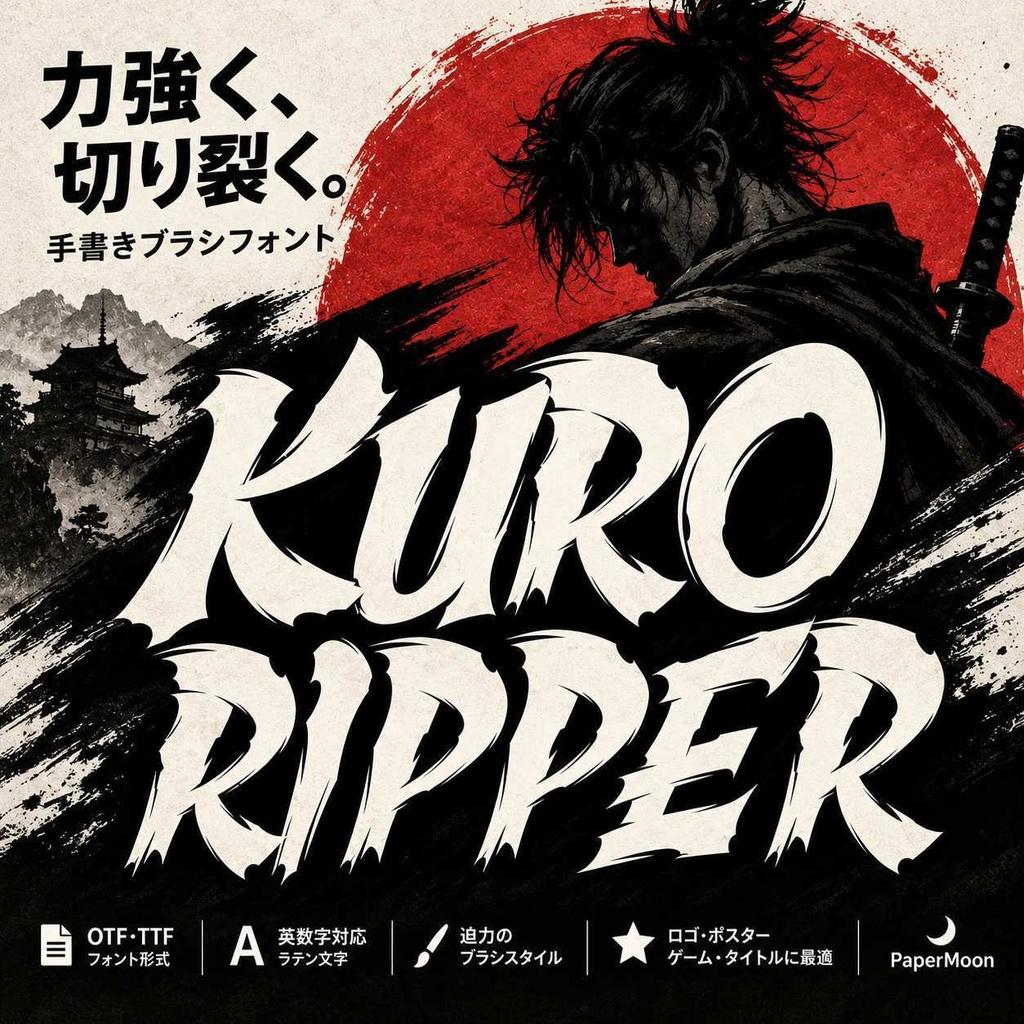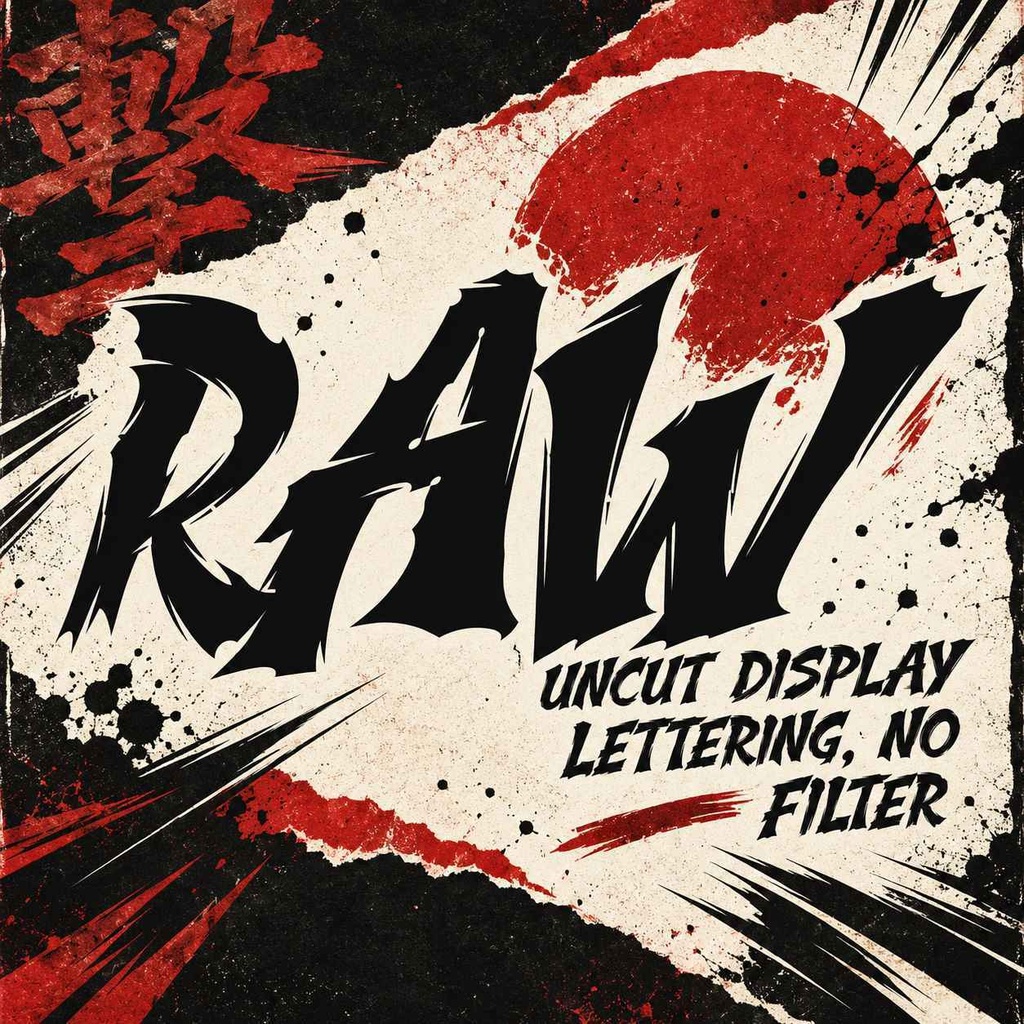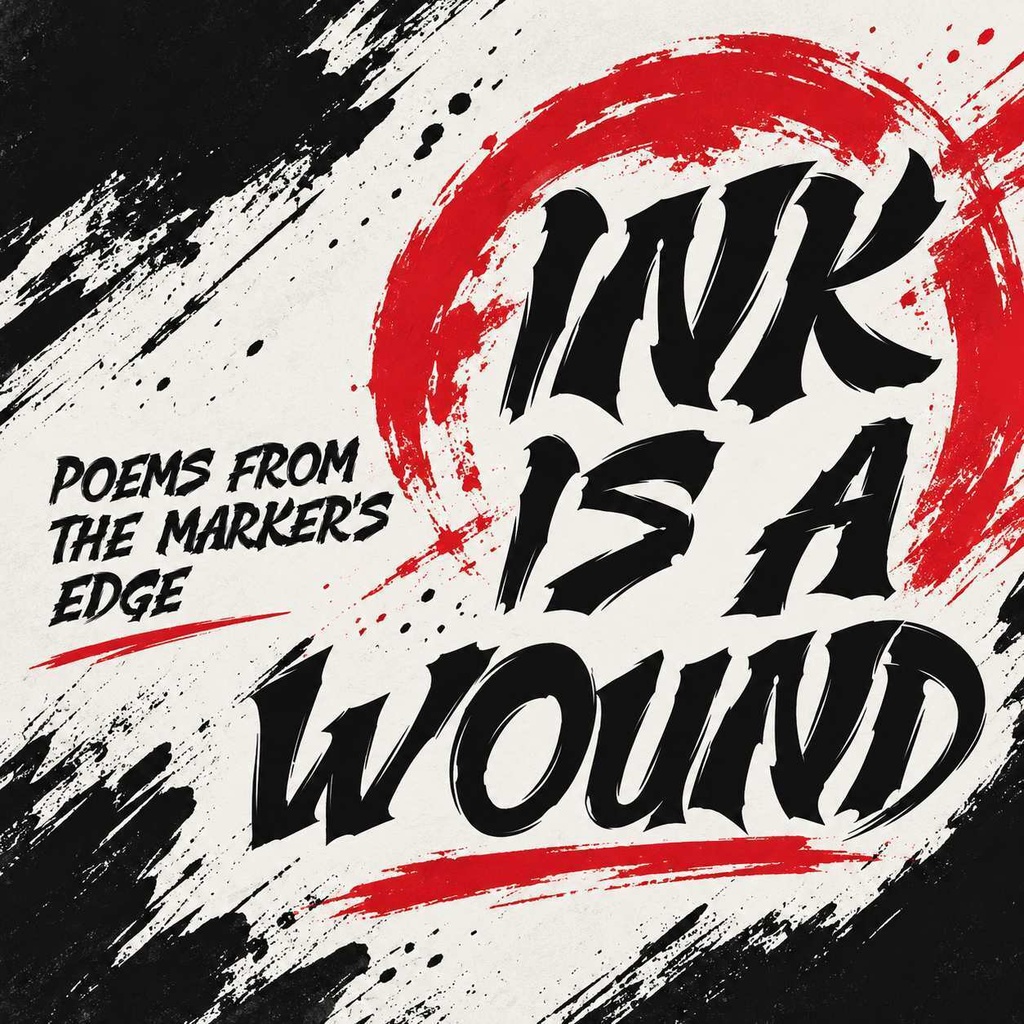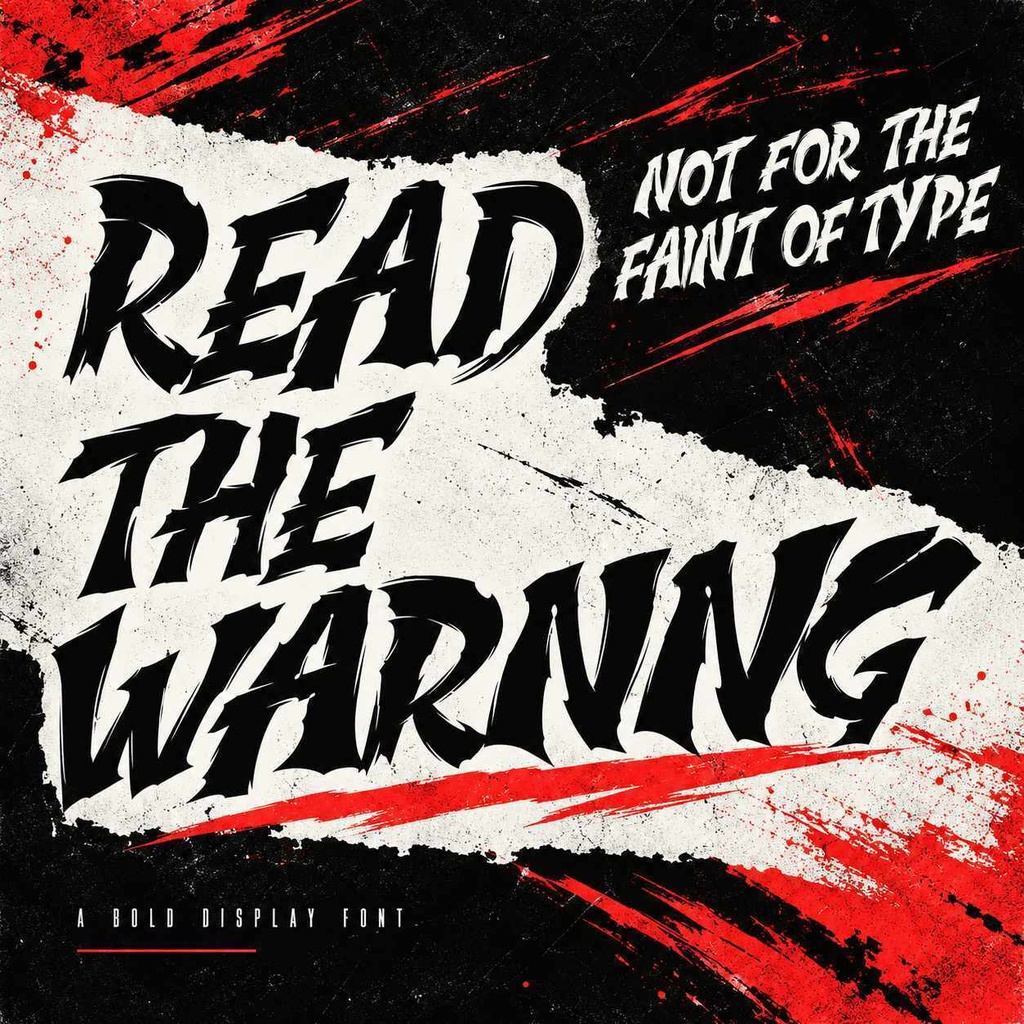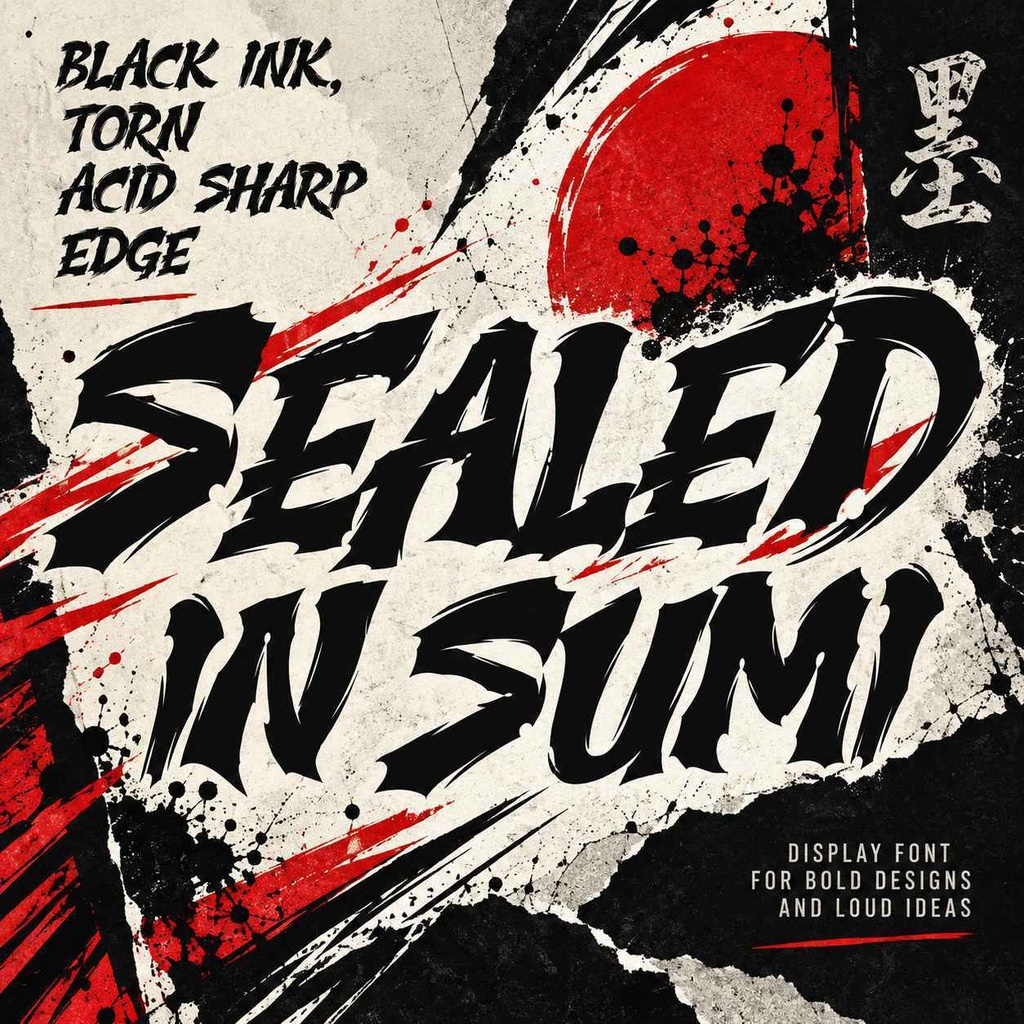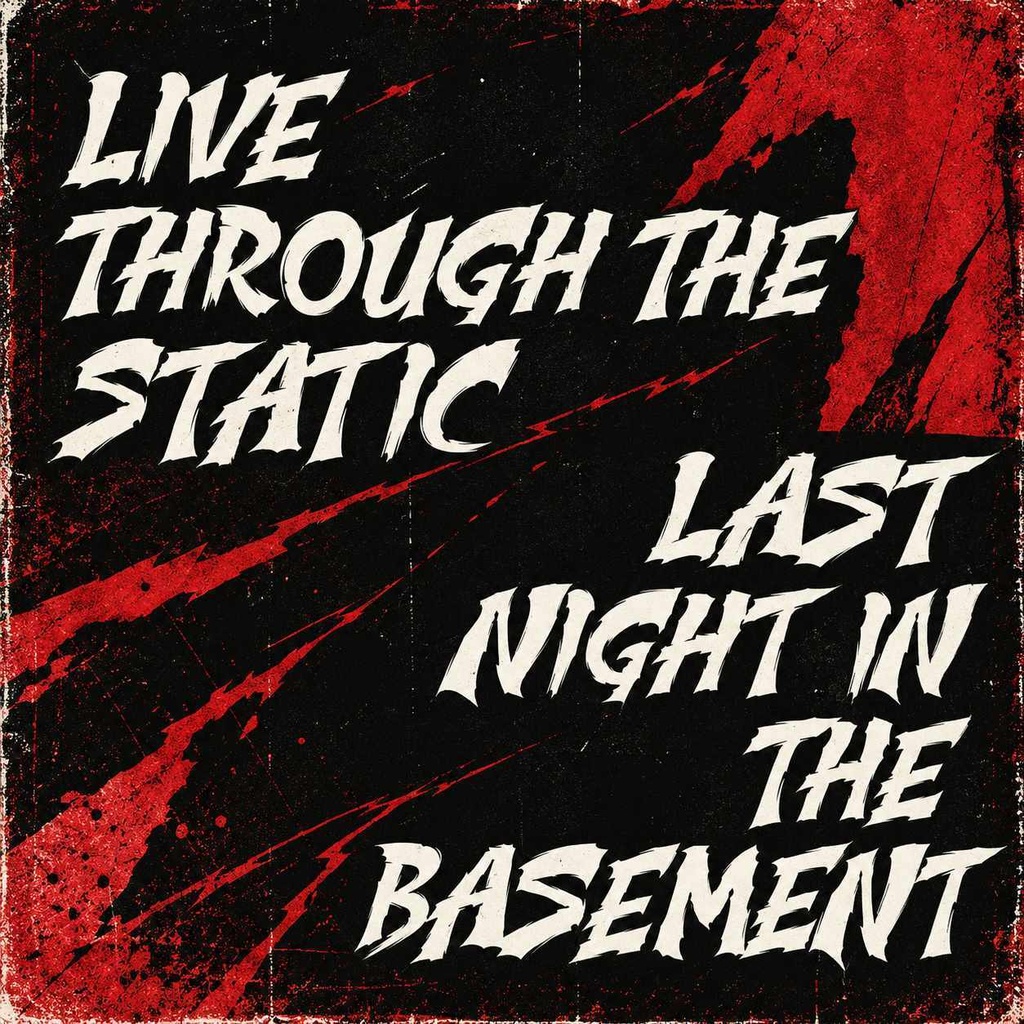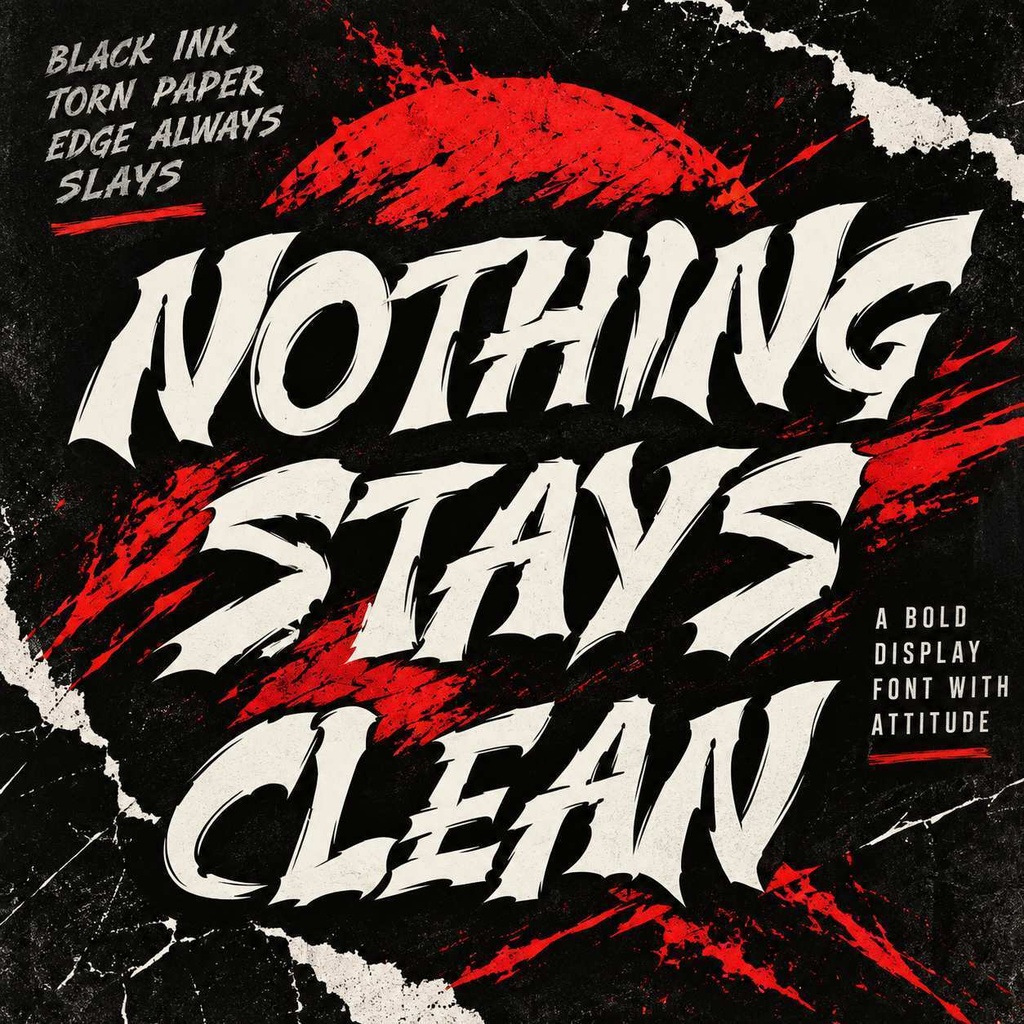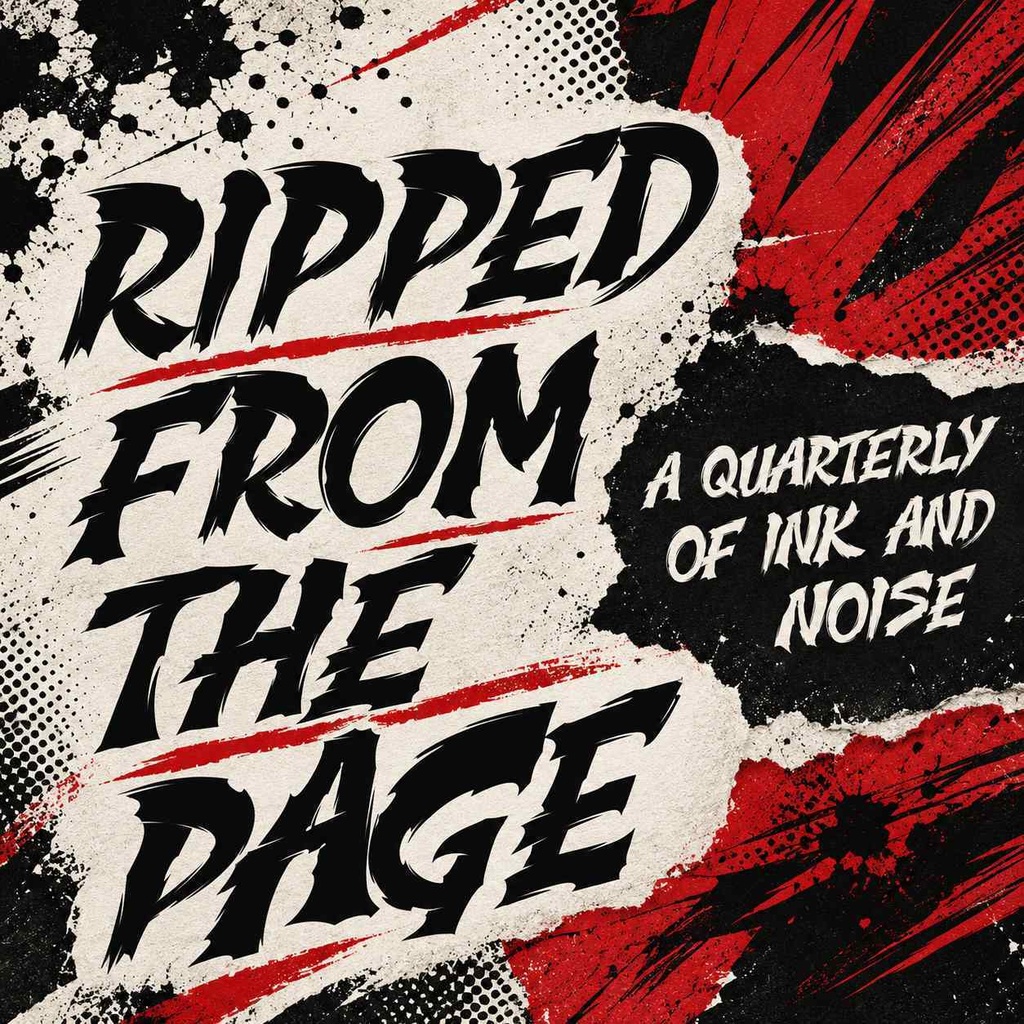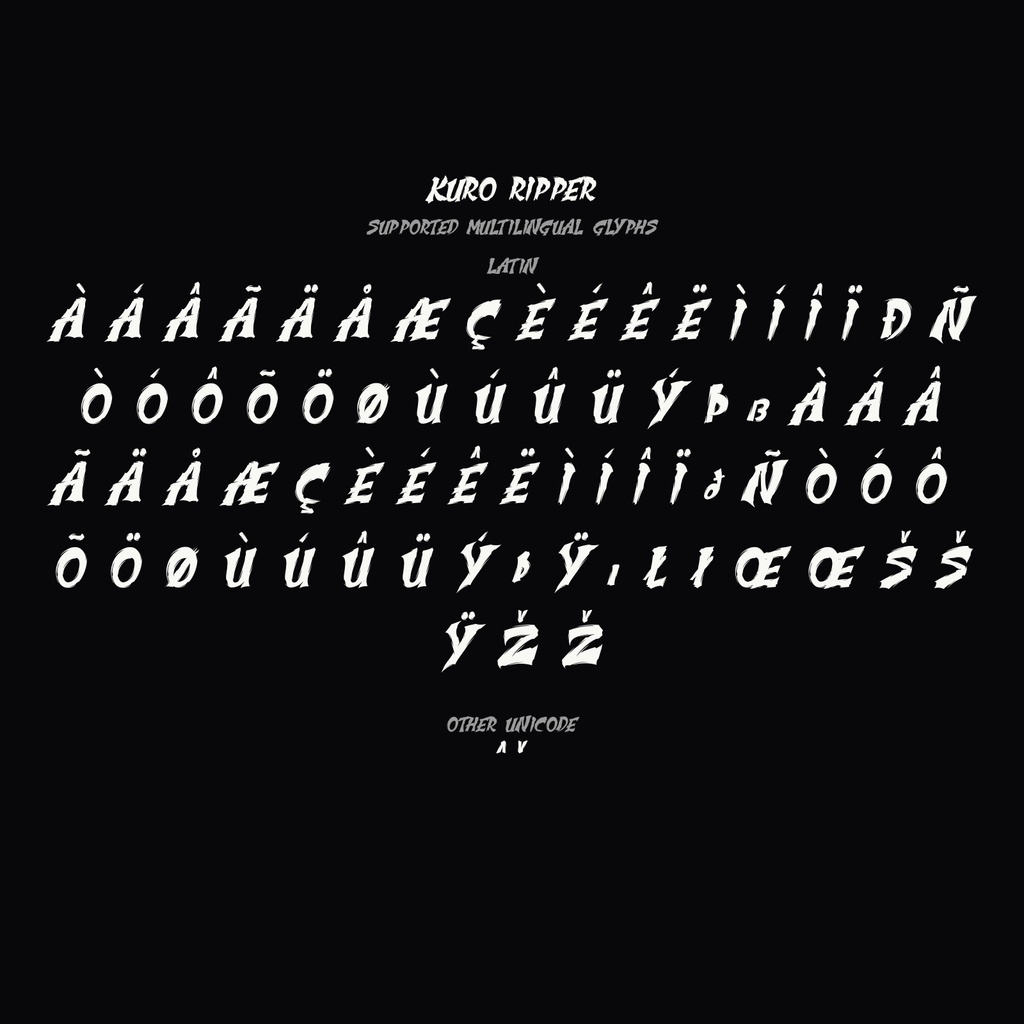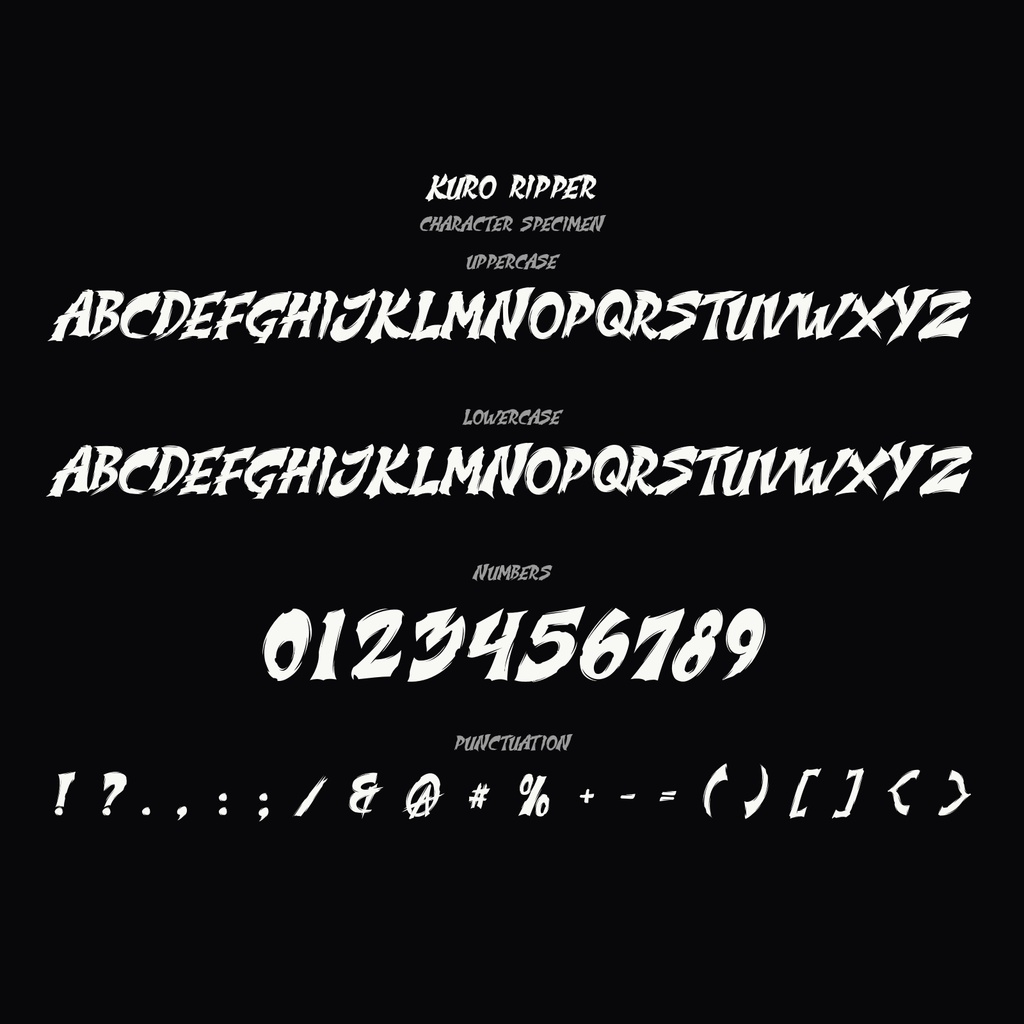
Kuro Ripper | ホラーマーカー欧文フォント | ロゴ・ポスター・アパレル向け
ホラー・マーカーの激しい筆致が生み出す、攻撃的で迫力あるディスプレイフォントです。Kuro Ripperは、トーンを裂くようなブロックストロークとY2Kカルチャーのスプラッタ美学を融合し、ロゴデザインやポスター、アパレル、ゲームタイトル、同人誌の表紙や見出しなどに強烈なインパクトをもたらします。 撕れたポスターの質感とスプレーマーカーの原始的なエネルギーを纏い、都会のストリートカルチャーからホラーマンガのパンチラインまで、あらゆるカードオブジェクトに反抗的な存在感を刻みます。デザインフォントとしての完成度と、タイポグラフィとしての表現力を同時に備えています。 ## 収録内容 Kuro Ripper本体フォント一式 ## 対応文字 英字(A-Z)および欧文基準文字、アクセント付き多言語文字、数字、句読点を収録。PUAエンコード対応。日本語、キリル文字、ギリシャ文字は含まれていません。 ## 用途 ロゴデザイン、ロゴ、バナー、ポスター、チラシ、ゲームタイトル、サムネイル、配信グラフィック、同人誌の表紙や見出し、見出し、アパレルデザイン、ブランドデザイン、広告、YouTubeのテロップやチャンネル見出しなど ## 形式 OpenType(OTF)、TrueType(TTF)、WOFF、WOFF2 ## 対応環境 macOS、Windows、Linuxの主要なデザインソフトウェアおよびテキストエディタに対応。Webフォント(WOFF/WOFF2)はウェブサイトでの使用に対応しています。ブラウザの互換性は製品環境に依存します。 ## 利用許諾 このフォントの商用利用は `Kuro Ripper | 商用利用 | Commercial Use` バリアントで提供されます。ビジネス、クライアント案件、有償プロジェクト、ブランド展開、広告、アパレル販売、グッズ販売など、収益を伴う用途には商用利用バリアントをご購入ください。 個人利用は無料キャンペーン中です。購入者自身の非営利プロジェクト、学習、練習、個人制作に限られます。 再配布、リセール、フォントデータ単体の転売、テンプレート埋め込み redistribution は許可されていません。詳細は商品ページのライセンス情報をご確認ください。